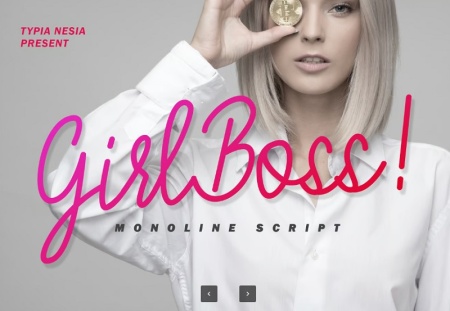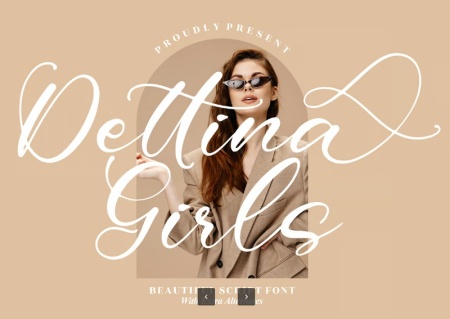
دانلود 3 فونت انگلیسی دخترانه Gold Girls
فونت انگلیسی دخترانه
فونت انگلیسی دخترانه از جی اف ایکس دانلود. در این مطلب از سایت مجموعه 3 فونت‌ انگلیسی دخترانه قرار گرفته شده است. این فونت ها با طراحی نرم و ظریف حس لطافت و زیبایی را منتقل می‌کنند. مناسب برای طراحی کارت‌های تبریک، دعوت‌نامه‌های عروسی، لوگو و برندینگ، شبکه های اجتماعی، وبلاگ‌ها و وب‌سایت‌ها، چاپ روی تی‌شرت، ماگ و غیره می باشد.
ویژگی های فونت انگلیسی دخترانه سایت جی اف ایکس دانلود
شامل 3 مجموعه فونت انگلیسی جدید و جذاب دخترانه
✅ نام فونت 1: Dettina Girls Script Font
✅ نام فونت 2: Girl Boss
✅ نام فونت 3: Gold Girls